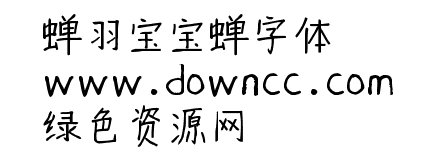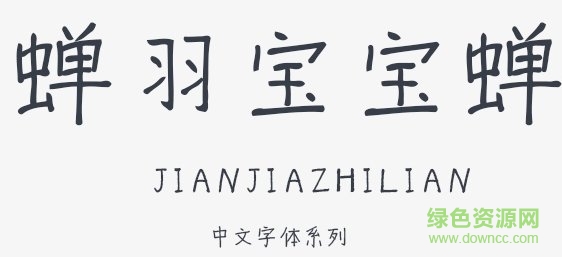
蟬羽寶寶蟬字體ttf是更為精簡端正的個(gè)性手寫字體,結(jié)構(gòu)端方筆畫細(xì)膩,整體連貫,部分字體帶著微小的差距,整體上比較和諧,快來綠色資源網(wǎng)試試吧!
蟬羽寶寶蟬簡體是一款個(gè)性手寫字體,字形樸實(shí)無華,自然天成,適用于媒體顯示和廣告設(shè)計(jì)等領(lǐng)域應(yīng)用。
蟬羽寶寶蟬簡體是蟬羽字體系列的硬筆書法字體,字跡兼具pop字體和卡通字體的風(fēng)格,無統(tǒng)一的模板,更顯隨意,給你的平面設(shè)計(jì)、編輯排版、廣告創(chuàng)意等帶來獨(dú)特呈現(xiàn)!